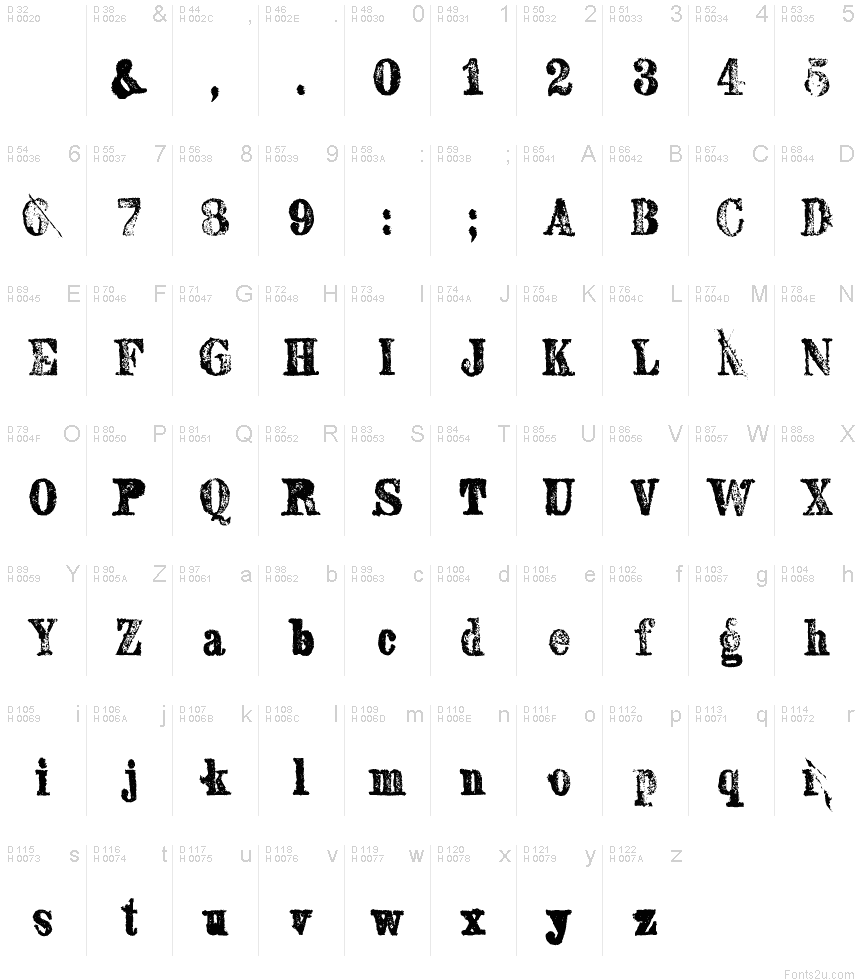
Sexton Serif od Polenimschaufenster fonts to darmowy, erodowany krój szeryfowy typu display, przypominający tusz, który z czasem zaczął się łuszczyć, rozmywać i wietrzeć. Litery wydają się surowe i stare, a jednocześnie żywe – masywne szeryfy rozpadają się na poszarpane krawędzie i wytarte wnętrza, co nadaje całości charakteru niczym z dawnej drukarni.
Idealnie pasuje do plakatów, okładek książek, grafik muzycznych, ulotek na Halloween i surowych nagłówków, gdzie klasyczny, czysty szeryf wydałby się zbyt grzeczny. Jako darmowy font, sprawdzi się również w krótkim brandingu, grafikach eventowych i dużych inicjałach, ponieważ jego zniszczona tekstura sama w sobie buduje odpowiedni klimat.